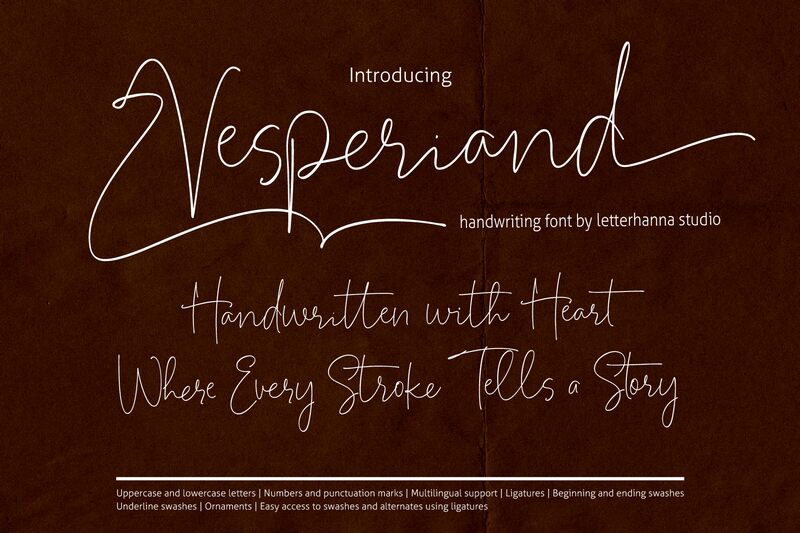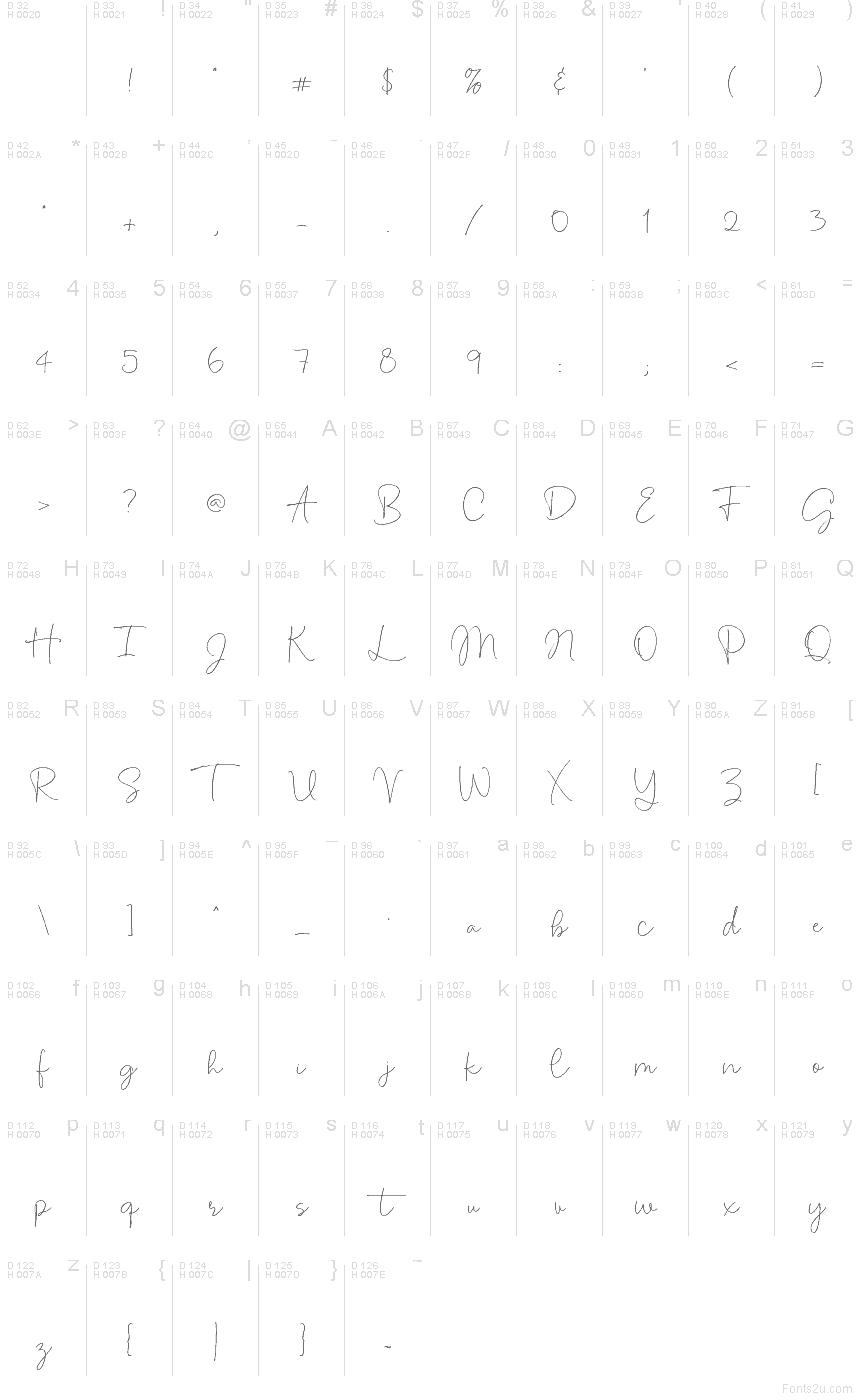
Vesperiand, creata da Rinaldo Hasibuan di Letterhanna Studio, è un font calligrafico gratuito dal carattere fresco, che ricorda una firma. I tratti sottili e ricchi di inchiostro, uniti alle connessioni lunghe e sinuose, conferiscono alle parole un'eleganza sussurrata, come se fossero state scritte rapidamente ma con sicurezza su carta liscia. Il ritmo rimane leggero e arioso, rendendolo raffinato anziché disordinato.
Vesperiand risplende su partecipazioni di nozze, packaging di profumi o cosmetici, loghi di boutique, menu di caffè, post social, grafiche con citazioni e intestazioni di inviti. Usala con una dimensione leggermente maggiore per mantenere nitide le sue linee delicate e accompagna questo font gratuito con un sans serif pulito, come Montserrat o Helvetica, per il testo di supporto.